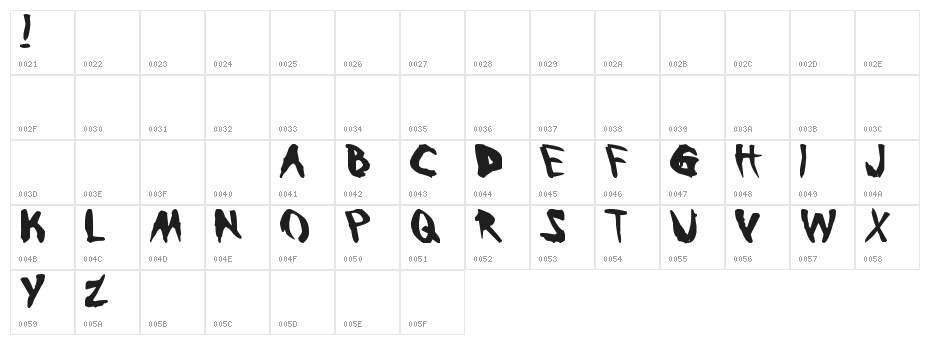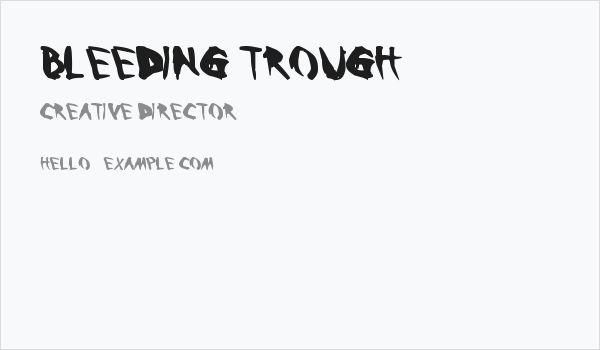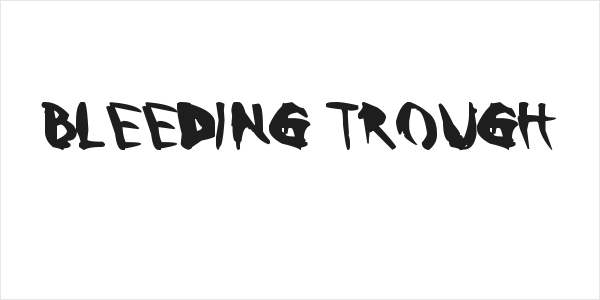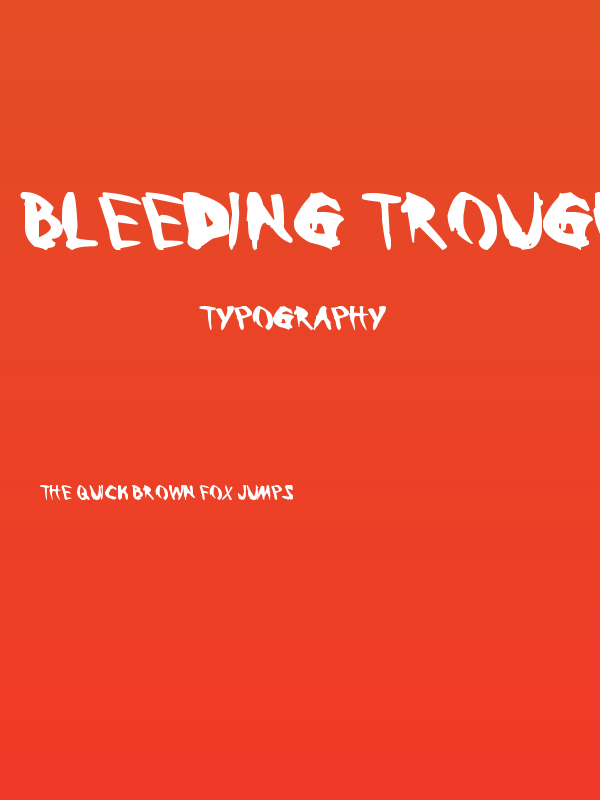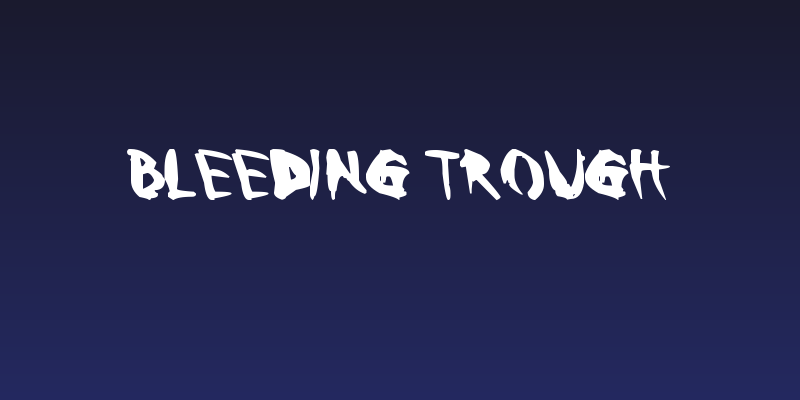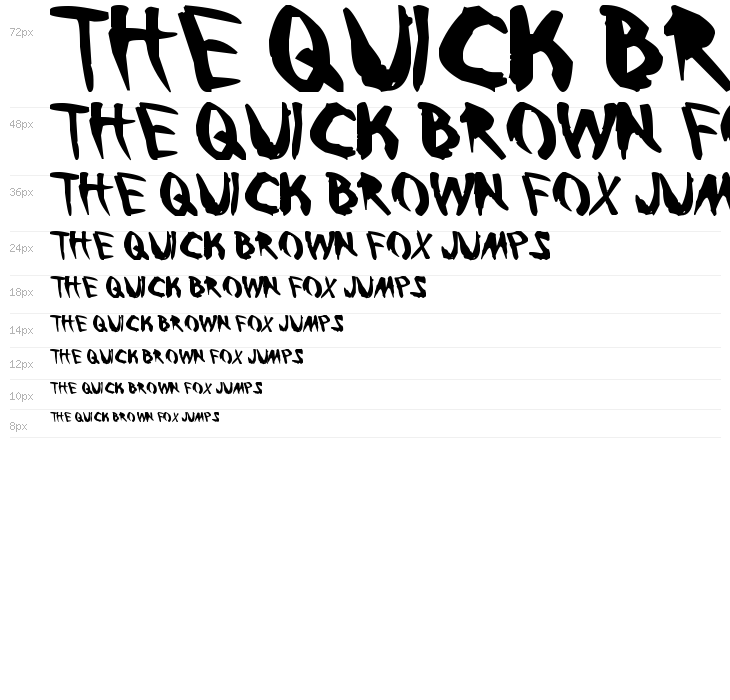
Bleeding Trough Font
| 名称 | Bleeding Trough |
| 分类 | Handwritten |
| 推荐项目 | Ideal for horror movie posters, edgy album covers, rebellious fashion branding, or any project needing a dramatic flair. |